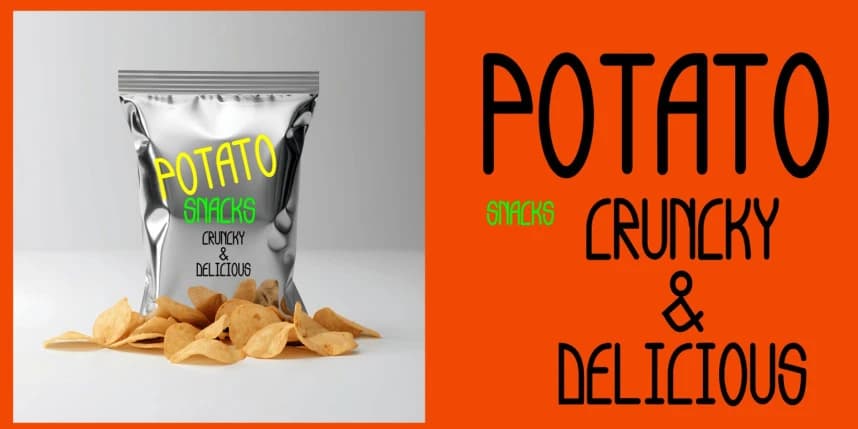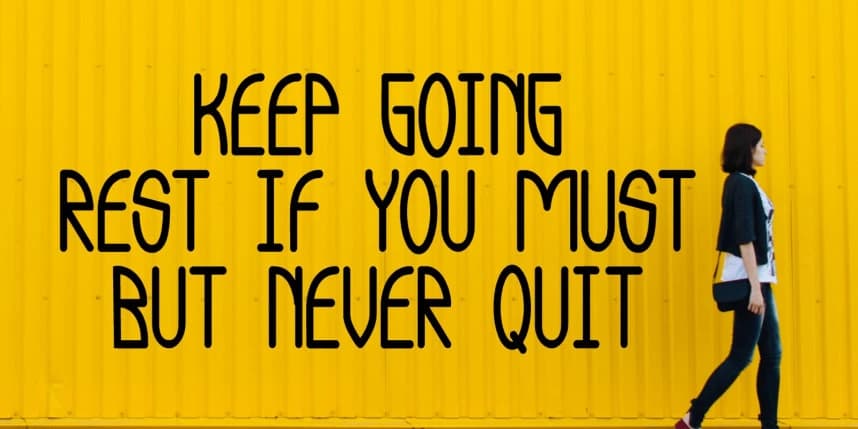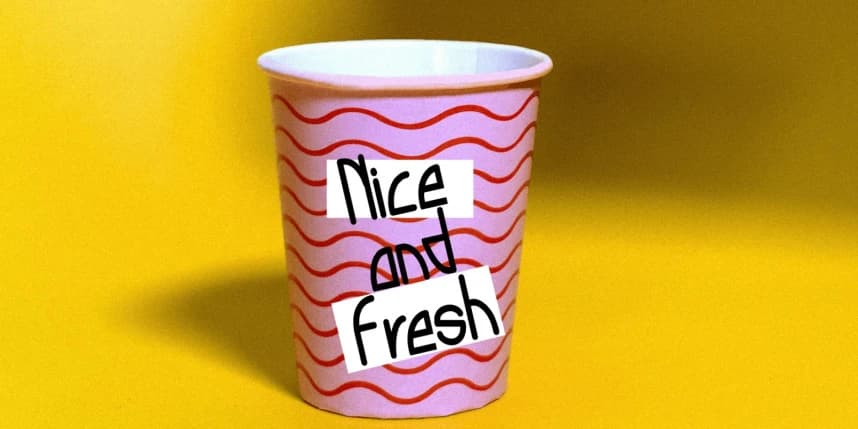
Staylo Font
STAYLO Font, güçlü bir görsel etki yaratmak için tasarlanmış cesur ve şık bir gösterim yazı tipidir. Modern hatları ve kendinden emin karakteriyle STAYLO anında dikkat çeker ve herhangi bir tasarım projesine kişilik katar.
STAYLO Font, güçlü bir görsel etki yaratmak için tasarlanmış cesur ve şık bir gösterim yazı tipidir. Modern biçimleri ve kendinden emin karakteriyle STAYLO, hemen dikkat çeker ve herhangi bir tasarım projesine kişilik katar.